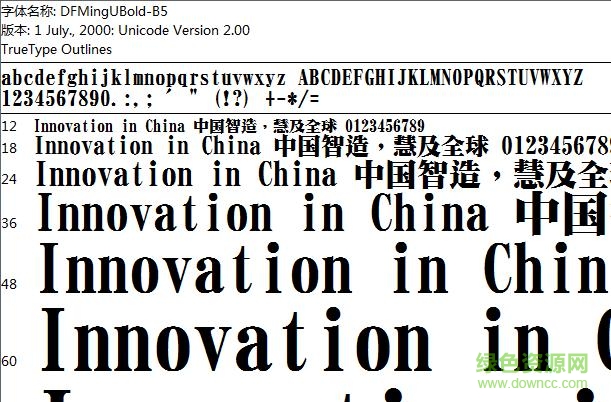
華康超明體簡(jiǎn)/繁體
華康超明體字體是一款仿造宋體打造的一款中文字體,字形與傳統(tǒng)的宋體相差不是很大,所以你看上去也會(huì)覺(jué)得很親切,有需要用到這款字體的朋友歡迎下載!
華康超明體字體簡(jiǎn)介
華康超明體字體是華康打造的一款宋體字體,是根據(jù)古代的印刷字體打造而來(lái),體的豎向線條較粗,橫向較細(xì),平時(shí)的書(shū)刊報(bào)紙使用的都是宋體字體!